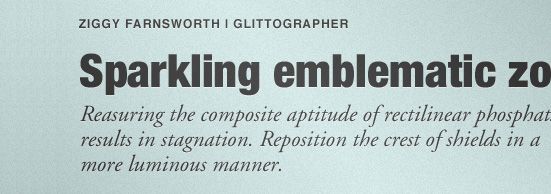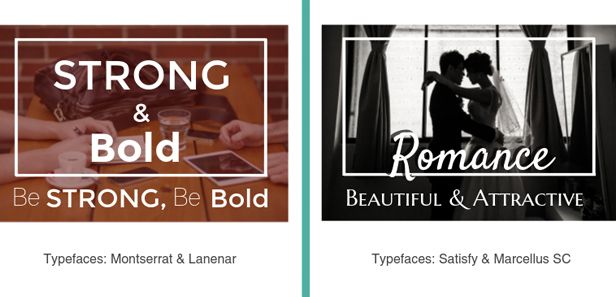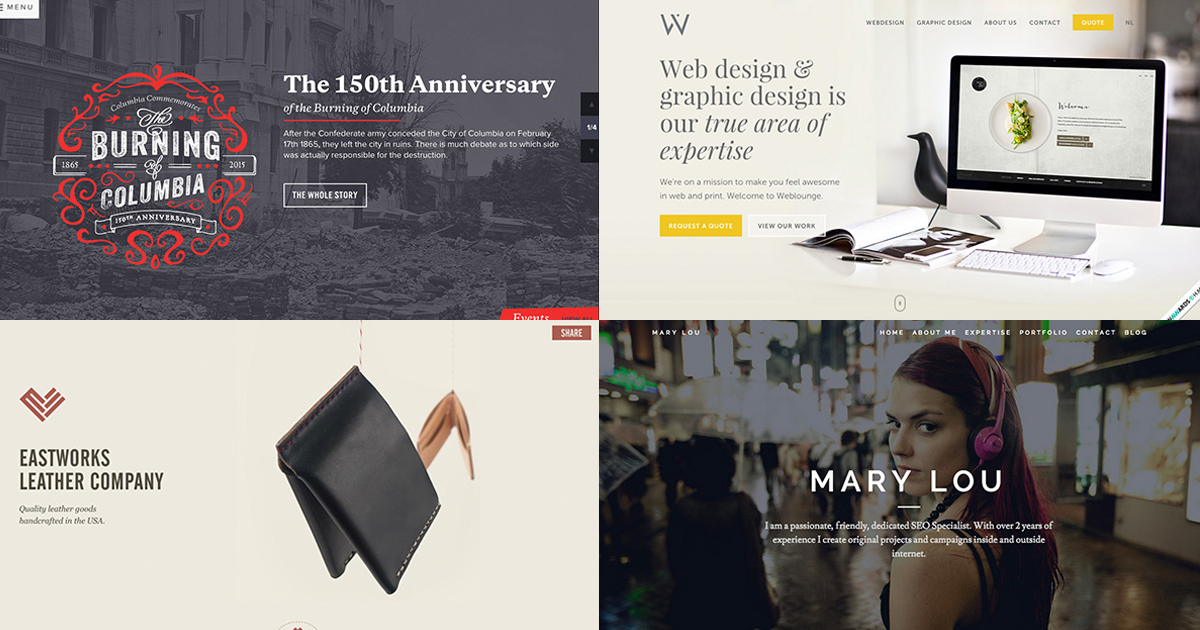
Kết hợp các kiểu chữ là cả một nghệ thuật.
Điều tuyệt vời nhất về nghệ thuật và thiết kế là mỗi khi bạn tạo ra một hình dạng, kiểu dáng mới, bạn có thể thỏa sức khám phá các phong cách, kĩ thuật và những sự phối hợp khác nhau để truyền tải đi một thông điệp. Như một người đã từng nói rằng: Phải hiểu được những điều cơ bản nhất của nghệ thuật thiết kế, bạn mới có đủ khả năng để bước qua ranh giới của các luật lệ.
Designer thường xuyên phải làm việc với rất nhiều font chữ khác nhau nhằm tạo ra một tổng thể thu hút và xây dựng phân cấp thị giác một cách hiệu quả. Trong trường hợp không có những luật lệ nghiêm ngặt hay các quy tắc khoa học để có thể áp dụng, bạn cần phải liên tục thử nghiệm và kiểm tra lại các kĩ thuật để có thể tạo ra được một cấu trúc typography ổn định. Bằng cách quan sát và học tập những phương pháp tốt nhất của quá trình thiết kế con chữ, bạn sẽ có khả năng chỉ ra được liệu những kiểu chữ nào khi kết hợp với nhau sẽ cho ra kết quả phù hợp nhất.
1. Những font bổ túc
Hầu hết các kiểu chữ đều có khả năng khơi gợi nên một phản hồi mang tính cảm xúc từ phía người dùng. Những kiểu chữ có xu hướng biểu đạt những trạng thái cảm xúc cũng như tính chất khác nhau, chúng cũng nên được kết hợp dựa trên sự phù hợp của những đặc tính đó. Tuy nhiên, trong một số trường hợp nhất định, những kiểu chữ ở hai thái cực đối lập lại có thể song hành cùng nhau một cách tương đối hiệu quả. Điểm khác biệt làm nên mỗi kiểu chữ thường mang lại sự cân bằng cho những kiểu chữ đối lập chúng và tạo nên một thiết kế hài hòa, tinh tế.
Ví dụ, nếu bạn đang thực hiện thiết kế với một font mang tính chất mạnh mẽ, đồ sộ (giống như font ở hình phía trên) thì hãy kết hợp nó với một font nhỏ gọn, thanh lịch. Điều này sẽ cho bạn khả năng tạo ra một thiết kế cân bằng, dễ chịu. Khi đưa ra quyết định kết hợp đó, bạn sẽ thường thấy rằng bản thân phụ thuộc nhiều vào cảm xúc cá nhân và điều này thì không sao cả. Hãy bình tĩnh. Việc tìm kiếm và kết hợp đúng font với nhau không hề đơn giản và đòi hỏi bạn phải luyện tập thường xuyên để có thể đạt đến cảnh giới đó.
2. Kết hợp giữa font chữ có chân và font chữ không chân
Đây là một kết hợp thuộc hàng kinh điển, được sử dụng tương đối hiệu quả trên cả các dự án website cũng như các dự án in ấn. Nếu bạn không có nhiều thời gian trong việc lựa chọn, hãy kết hợp giữa một font serif (font chữ có chân) và một font sans serif (font chữ không chân). Điều này sẽ luôn đảm bảo tính rõ ràng cho nội dung văn bản của bạn. Ví dụ, nếu bạn nhìn vào bài báo phía dưới, bạn có thể thấy ngay rằng Trade Gothic là một kiểu chữ năng động và thanh lịch trong khi Bell Gothic. Ngược lại, có một sự hiện diện áp đảo. Việc kết hợp hai kiểu chữ này lại có lẽ sẽ không phải là lựa chọn tối ưu nhất để nhận dạng nội dung văn bản.
3. Kết cấu tương phản
Một trong những lý do giải thích cho sự hiệu quả của việc kết hợp giữa font chữ có chân và font chữ không chân là bởi vì chúng có khả năng tạo ra một sự tương phản thị giác khi đứng cạnh nhau. Sự tương phản có thể đạt được theo nhiều phương pháp - sử dụng màu sắc, các phong cách, độ dày/mỏng của yếu tố, kích thước và khoảng cách. Nếu bạn nhìn vào ví dụ phía trên, bạn sẽ thấy cách mà những chữ với các nét bo tròn và uốn cong trông ổn hơn khi kết hợp với những chữ có các đường nét mảnh mai, thanh lịch.
4. Thiết lập hệ thống phân cấp thị giác
Khi đang thực hiện một dự án thiết kế, bạn cần xây dựng phân cấp thị giác không chỉ cho bố cục và hình ảnh mà còn cho cả nội dung văn bản. Cách này giúp người xem đọc được những phần nội dung quan trọng nhất trong một trang. Hướng làm khác là trước khi thiết kế, bạn hãy xem qua một lượt những thông tin nào được cho là cần thiết trong bố cục.
Một khi đã nhận định được rõ đâu là phần cần được làm nổi bật, bạn sẽ có khả năng đưa ra những quyết định thiết kế có chủ đích hơn. Một số nền tảng xuất bản truyền thống như giấy báo, tạp chí hay tập san, tất cả đều là những ví dụ tuyệt vời cho việc áp dụng phân cấp thị giác lên bố cục của trang.
5. Giới hạn số lượng font chữ
Các chuyên gia đề xuất rằng chúng ta chỉ nên sử dụng tối đa từ 2-3 font chữ trong một bố cục. Điều này sẽ luôn luôn đảm bảo cho bạn về tính rõ ràng và dễ đọc của văn bản. Mặc dù một vài dự án có thể yêu cầu bạn trau chuốt thêm các sự kết hợp của font chữ. Nếu bạn nằm trong hoàn cảnh đó, hãy cố gắng tạo ra sự hài hòa và tính liên kết trong thiết kế của bạn đồng thời tránh khiến nó trở nên hỗn tạp và lộn xộn.
6. Cân nhắc về bối cảnh
Việc lựa chọn font chữ nào phụ thuộc phần lớn vào dự án thiết kế mà bạn đang thực hiện. Thứ nhất, nó cần phải rõ ràng và hiển thị theo đúng kích thước. Phong cách của font chữ cũng đóng một vai trò quan trọng trong việc xây dựng sắc thái của cả dự án. Đặc điểm của font chữ nên tương xứng với thông điệp được truyền tải. Đôi khi, bạn sẽ cần những font chữ thực sự nổi bật trên bố cục, khi khác thì bạn lại mong muốn một cái gì đó trung tính, nhã nhặn hơn.
7. Phân chia các vai trò
Một cách đơn giản để kết hợp các kiểu chữ đó là chỉ định vai trò cụ thể cho từng kiểu chữ. Bạn có thể thực hiện điều này bằng cách chỉ định kiểu chữ in đậm dành cho các tiêu đề, kiểu chữ mỏng dành cho phụ đề và quay trở lại trung tính dành cho các đoạn văn bản chính. Cuối cùng, chúng đều được sử dụng để tạo thành một thiết kế thống nhất. Khi bạn chỉ định những vai trò này cho các font chữ, bạn có thể xác định được hệ thống phân cấp typography nhằm thu hút sự chú ý của người xem đến các yếu tố quan trọng nhất trong thiết kế.
"Practice makes perfect"
Luyện tập tạo nên sự hoàn hảo
Nghệ thuật kết hợp kiểu chữ phụ thuộc tất cả vào việc sử dụng trực giác của bạn, thử nghiệm và đón nhận các rủi ro. Chúng tôi hy vọng rằng những lời khuyên này sẽ giúp bạn hiểu rõ hơn các quy luật cơ bản và những tình huống nào cần phải tránh để có thể tạo ra sự kết hợp tuyệt vời nhất có thể.